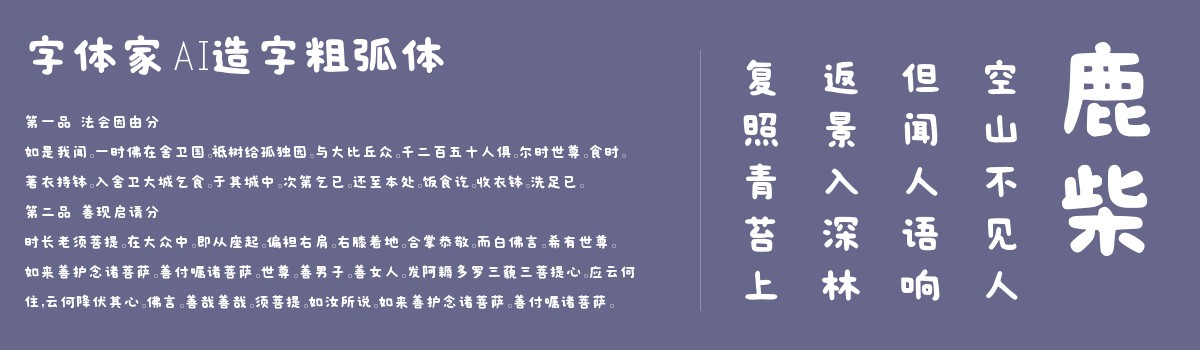
字体家AI造字粗弧体
字体家AI造字粗弧体是一款由字体家AI神笔造字生成的艺术字体,笔画粗壮且均匀,起收笔与转角处皆为流畅圆弧,无棱角。结构饱满敦实,线条柔和连贯,如圆润积木般扎实,又因弧线透着灵动,整体呈现稳重亲切的视觉质感,无攻击性却显可靠。适合用于一些广告标题、平面文案、海报标题、网页广告用字的编辑。